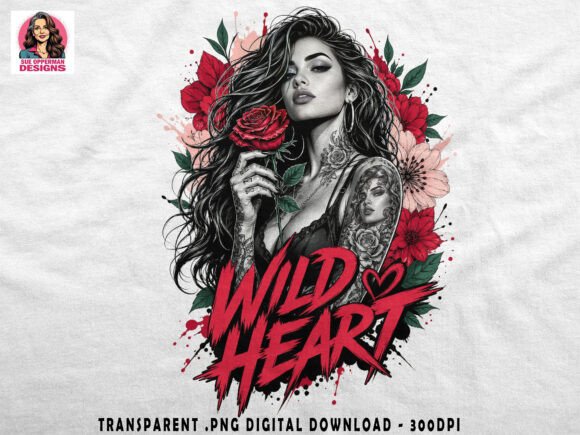
Wild Heart Rose Girl Aesthetic
Wenn Sie nach hochwertigen Assets wie Wild Heart Rose Girl Aesthetic suchen, ist dieses Premium-Paket eine fantastische Wahl für Ihre kreativen Projekte.
Egal, ob Sie POD-Produkte (Print on Demand), Hochzeitseinladungen oder Social-Media-Grafiken erstellen, Wild Heart Rose Girl Aesthetic ist die ideale Wahl.